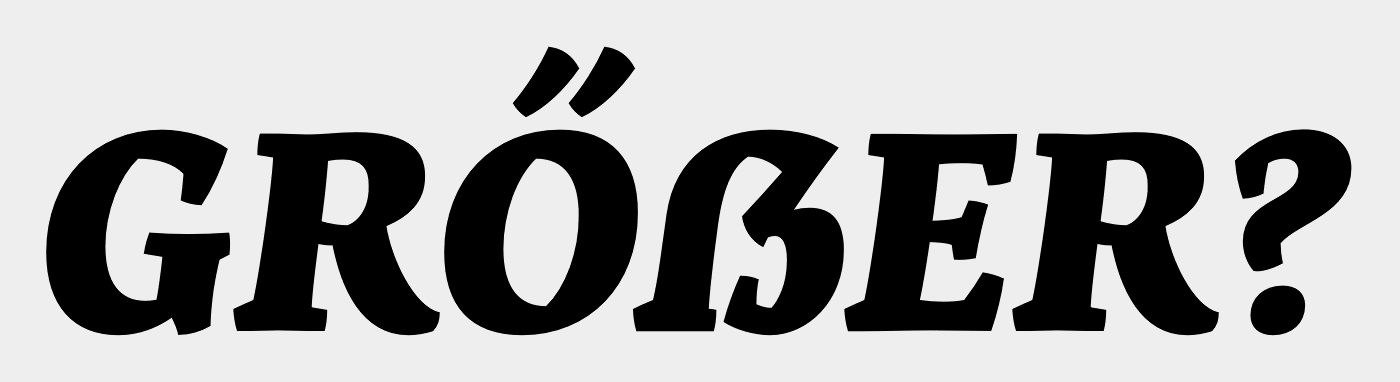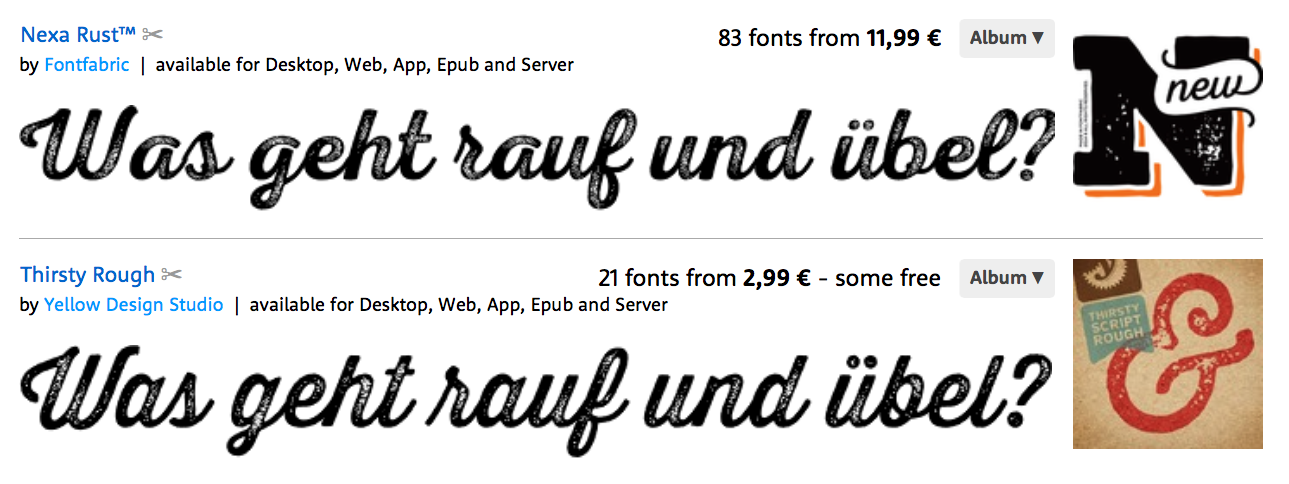
sehr nette ziffern, die christmas numerals, gibt’ hier gratis.
Die haben ja alle ein nettes Grinsen, gerade die 5 ist sehr feist  :hammer:
Cool! Was empfiehlst Du denn davon? Hast Du Präferenzen?
Meine »Stars« sind nicht wirklich dabei – aber hattest Du letztens nicht mit der Haas geliebäugelt? Dann könntest Du hier zumindest günstig an ein paar Schnitte zum »Testen/Einsteigen« erwerben. Die Supria ist ja eigentlich auch nicht ganz schlecht, aber da fehlen mir eindeutig die dünnen Schnitte.
Ja, trotzdem lieben Dank für Dein Antwort! Ich hatte mich auch durch die Angebote geschaut und zum Teil waren die Schriften nicht so mein Ding, oder 200 € für eine Schrift, die ich nicht unbedingt dringend brauche, waren mir zu viel. Bei der Haas habe ich gedacht, dass die da angebotenen Schnitte mir nicht so richtig viel gebracht hätten und die Helvetica hätte mich tatsächlich gereizt – wenn es denn eine Neue Helvetica gewesen wäre. Ich habe es dann schlussendlich gelassen. Ich habe in letzter Zeit ja auch ziemlich zugeschlagen bei Schriften und werde jetzt erstmal warten, bis mich eine mal wieder so richtig vom Hocker reißt.
Übrigens: Da wir hier doch schon einige Male über die Centrale Sans gesprochen haben: Ich arbeite seit heute für einen Kunden mit der Schrift und habe so die Gelegenheit, sie auszuprobieren. Ich werden dazu mal eine Rückmeldung geben, wenn ich ein Gefühl für die Schrift bekommen habe.  :-D
Habt Ihr gesehen, dass die Voltage von Laura Worthington momentan zu einem Sonderpreis zu haben ist?
Ich finde ja, die hat was, die Schrift! Drei Schnitte für zusammen 13,98 €.
Was haltet ihr denn von der Servus Slab? Gerade entdeckt, nur noch bis heute für $29 (USD) statt $290 für Aufrechte und echte Kursive in 9 Stärken. Mit ẞ, Kapitälchen, verschiedenen Ziffernsätzen und einem anscheinend ordentlichen Sprachausbau.
Auf den ersten Blick erscheint sie mir sehr sympathisch und nicht so »kantig und hart« wie manche Slabs. Von dieser Sorte habe ich noch kaum was. Seht ihr irgendwelche Probleme (mit der Schrift an sich oder der Foundry)?
(Das ő oben ist ein ungarisches zum Testen.)
die servus slab sieht für mich sauber aus. das einzige, was ich bedaure: es gibt kein muster-pdf, aus dem man sich ein paar zeilen im fließtext ausdrucken kann. das würde ich immer erst sehen wollen, bevor ich eine schrift kaufe. walter tracy hatte recht, als er sagte: »A great typeface is not a collection of beautiful letters, but a beautiful collection of letters.«
Was sagt Ihr denn zur Riga von Ludwig Uebele (69,80 € statt 349 €) und zur Quire Sans von Monotype (99 € statt 499€)?
Riga
Aus diesem Genre sprechen mich andere mehr an, zum Beispiel die FF Profile, TheSans, …
Quire
Ja, an der bin ich jetzt auch schon paar mal hängen geblieben. Schön freundlich, warm und lebendig. Aber auch hier würde ich trotz eckigen Punkten eher zur Auto tendieren, da diese zum Beispiel ein rundes l und ein Versaleszett enthält und etwas kerniger wirkt. Kommt sicher auch etwas darauf an, was man schon so im Schatzkästchen hat und welche Spielarten noch fehlen.
Was haltet ihr denn von der Servus Slab? Gerade entdeckt, nur noch bis heute für $29 (USD) statt $290 für Aufrechte und echte Kursive in 9 Stärken. Mit ẞ, Kapitälchen, verschiedenen Ziffernsätzen und einem anscheinend ordentlichen Sprachausbau.
Auf den ersten Blick erscheint sie mir sehr sympathisch und nicht so »kantig und hart« wie manche Slabs. Von dieser Sorte habe ich noch kaum was. Seht ihr irgendwelche Probleme (mit der Schrift an sich oder der Foundry)?
(Das ő oben ist ein ungarisches zum Testen.)
Also ich habe mal der Clavo vom gleichen Anbieter gekauft, und war nicht wirklich begeistert. Es hat auf dem ersten Blick viele nette Eigenschaften, aber leider ist die Qualitätskontrolle nicht sehr gut, es fehlt sozusagen ein bisschen Feinschliff in vielen Bereichen wie Zurichtung, Hinting etc.
Ich würde die servus also nicht unbedingt empfehlen
Nah dran und doch irgendwie weit genug weg ... aber einen komischen Beigeschmack gibt es irgendwie schon ...
... und bin mir auch nicht sicher, wer von wem ... ?!?